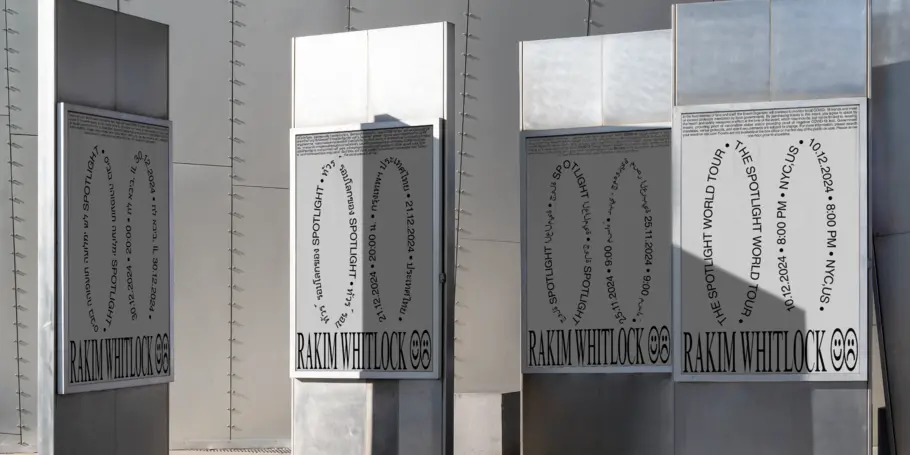
8 erreurs à éviter lors de la création de votre marque.
En tant que designer, c’est toujours exaltant de créer une nouvelle marque ou de refaire le branding d’une marque existante. Vous avez une liberté de création, de stratégie, c’est l’occasion de montrer votre talent !
En plus de décider de la palette de couleurs et du style iconographique, vous devez choisir une police de caractères qui deviendra le pilier de la marque. Mais le choix d’une police de marque ne devrait pas seulement se baser sur l’esthétique.
Peu importe à quel point la typographie que vous avez choisie est attrayante ou distinctive, si elle fonctionne mal, vous le regretterez. Vos collègues rencontreront des frustrations et seront forcés de trouver des solutions de rechange pour faire leur travail, quitte à se tourner vers des polices non autorisées. Au bout d’un moment, des incohérences typographiques vont émerger et diluer la belle marque que vous avez mis du temps à créer. Votre audience, elle aussi, s’en apercevra. Sa perception de la qualité de la marque s’en trouvera dégradée. Cela nuira au sentiment de confiance que vous cherchez à instaurer.
Vous souhaitez que l’histoire s’écrive autrement ? Il vous suffit d’éviter ces quelques erreurs courantes lors du choix d’une typographie.
Erreur n°1 : Une police de marque qui oublie l’avenir.
Ne perdez jamais de vue une chose. La marque que vous créez n’est pas seulement faite pour aujourd’hui. Votre branding doit être pensé pour durer plusieurs années. Considérez chaque endroit où la marque pourrait exister à l’avenir. Posez-vous les questions suivantes :
● Dans quelles régions du monde cette entreprise pourrait-elle se développer ?
● À quelles audiences pourrait-elle avoir besoin de s’adresser ?
● Sur quels supports cette typographie devra-t-elle fonctionner ?
● Quel type d’information la police de caractères choisie doit-elle transmettre ?
Plus vous anticipez sur ces points, plus vous serez efficace au moment de choisir la bonne police de marque.
Erreur n°2 : choisir une police en négligeant les autres langues.
Vous vous concentrez sur la langue principale de votre entreprise, et c’est bien naturel. Mais vous ne devez pas oublier de penser à toutes les langues que votre police de caractères devra couvrir à l’avenir. En plus de prendre en compte l’expansion géographique de votre marque, il est également intéressant de considérer les langues qui pourraient être utilisées par vos clients et vos employés actuels et futurs.
Si vous choisissez la mauvaise police de caractères, certains caractères spéciaux, diacritiques ou signes peuvent manquer. L’apparence à laquelle vous tenez pourrait ne pas être transposée dans d’autres langues.
Si vous pensez que votre marque va être amenée à communiquer dans de nombreuses langues, optez pour une famille de polices bien développée. C’est par exemple le cas de SST qui s’étend sur 93 langues, ou encore d’Avenir Next World et de Neue Frutiger® World qui couvrent plus de 150 langues.
Erreur n°3 : se contenter d’un jeu de caractères inadéquat.
La plupart du temps, vous n’avez besoin que de lettres minuscules et majuscules, accompagnées d’une poignée de signes de ponctuation « ordinaires ». Mais une police de marque doit inclure bien plus que cela pour répondre aux besoins d’un branding. Fractions, Diacritiques et Ligatures. Signes de ponctuation variés et de symboles monétaires.
Prenez un moment pour évaluer le jeu de caractères de toutes les polices de caractères que vous envisagez d’utiliser. Cela vous permettra de vous assurer qu’elle est capable de remplir les tâches qui lui sont confiées.
Erreur n°4 : l’esthétique au profit de la fonctionnalité.
De nos jours, les polices doivent être performantes sur tous les types d’appareils, de navigateurs, de programmes et de systèmes d’exploitation. Assurez-vous que vos polices de marque répondent aux normes de performance les plus élevées sur tous les tableaux.
Si vous cherchez une bonne indication des performances d’une police, le format OpenType en est une. Les polices OpenType, grâce à leurs structures de fichiers, ont une meilleure fonctionnalité. Elles offrent une compatibilité multiplateforme et des caractéristiques telles que les ligatures automatiques, les glyphes alternatifs et les jeux de caractères étendus.
La vitesse de chargement est un autre aspect important concernant la fonctionnalité des polices pour le Web. Vous devez choisir des polices qui s’afficheront rapidement lorsqu’elles seront sollicitées. Des outils de développement Web comme GiftOfSpeed peuvent vous aider à évaluer les temps de chargement et vous pouvez améliorer la performance avec un codage approprié.
Erreur n°5 : passer à côté d’une police de caractères réputée.
Il est facile de se laisser séduire par une toute nouvelle police de caractères. Mais souvent, les versions récentes ont des fonctionnalités encore relativement limitées.
En revanche, une famille de polices bien établie a tendance à être plus robuste, comme c’est le cas de Gotham ou d’Helvetica Now. Si vous hésitez à choisir une police aussi connue, rappelez-vous qu’il existe de nombreuses façons d’être expressif et distinctif avec une famille de caractères bien développée. Une grande variété de graisses, de chasses, de styles et de caractères alternatifs peut vous permettre de créer un branding unique avec une police classique.
Erreur n°6 : ne pas voir assez grand, ou petit.
Même si, aujourd’hui, votre marque n’apparaît pas sur les panneaux publicitaires des autoroutes, pourrait-elle en avoir besoin dans quelques années ? Comment votre police de caractères se comporterait-elle dans ce cas ? Envisagez toutes les possibilités :
● Présentations PowerPoint.
● Écrans de montre connectée.
● Publicité extérieure (aéroports, bus, métro…).
● Stands de salons professionnels, bannières, goodies.
● Mini caractères pour clauses de non-responsabilité et notes de bas de page.
Si vous avez l’intention d’utiliser une seule et même police de caractères, assurez-vous qu’elle a été conçue avec un système optique pour garantir son bon fonctionnement dans tous types de cas : textes, affichages et micro-formats.
Vous pouvez également envisager d’utiliser des polices variables. Elles offrent une polyvalence sans précédent, car vous pouvez ajuster les graisses, les chasses, l’inclinaison, la taille et le style selon vos besoins.
Erreur n°7 : ne pas tenir compte de vos collègues.
Choisir une police de caractères pour les cartes de visite et la signature des mails de l’entreprise, c’est bien. Mais vous devez aussi envisager toutes les façons dont les différents employés – les débutants aux cadres supérieurs – vont être amenés à l’utiliser.
Demandez au service marketing de vous parler de ses objectifs annuels. Discutez avec les responsables financiers de leurs diagrammes, tableaux et graphiques. Découvrez les besoins des RH, depuis l’étape de recrutement jusqu’à la gestion des départs à la retraite. Assurez-vous que votre police est à la hauteur de la tâche.
Erreur n°8 : se contenter du standard au lieu d’opter pour le pro.
Vous remarquerez que certains noms de polices comportent le suffixe Std (pour Standard) ou Pro (et pour Professionnel). Ces deux désignations ne signifient pas tout à fait la même chose d’une fonderie à l’autre, mais de manière générale, une version Pro offre :
● Une prise en charge OpenType.
● Plus de langues.
● Des options supplémentaires pour les ligatures, les obliques, les ornements, les petites capitales et les icônes.
● Des alternatives pour le titrage, les fractions, les chiffres et les styles.
Les versions Pro offrent plus de fonctionnalités et sont donc plus chères. Mais l’investissement en vaut la peine si celles-ci font partie de vos besoins. Vous obtiendrez une typographie plus robuste et l’assurance de couvrir toutes vos bases.
Choisissez judicieusement votre typographie et soyez heureux.
Ces erreurs sont courantes lorsqu’il s’agit de choisir une police de marque dans le cadre d’un branding. Mais si vous faites preuve d’un peu de prudence dès le début de votre projet, vous pouvez éviter un tas de problèmes. Vos choix de polices seront performants et votre marque sera solide pendant des années. Il suffit de veiller aux éléments mentionnés ci-dessus, et en particulier :
● Essayez d’anticiper tous les cas d’utilisation de votre police de marque, même futurs.
● Comprenez les besoins des différents services de votre entreprise.
● Testez rigoureusement chacune des polices de caractères de votre première sélection.